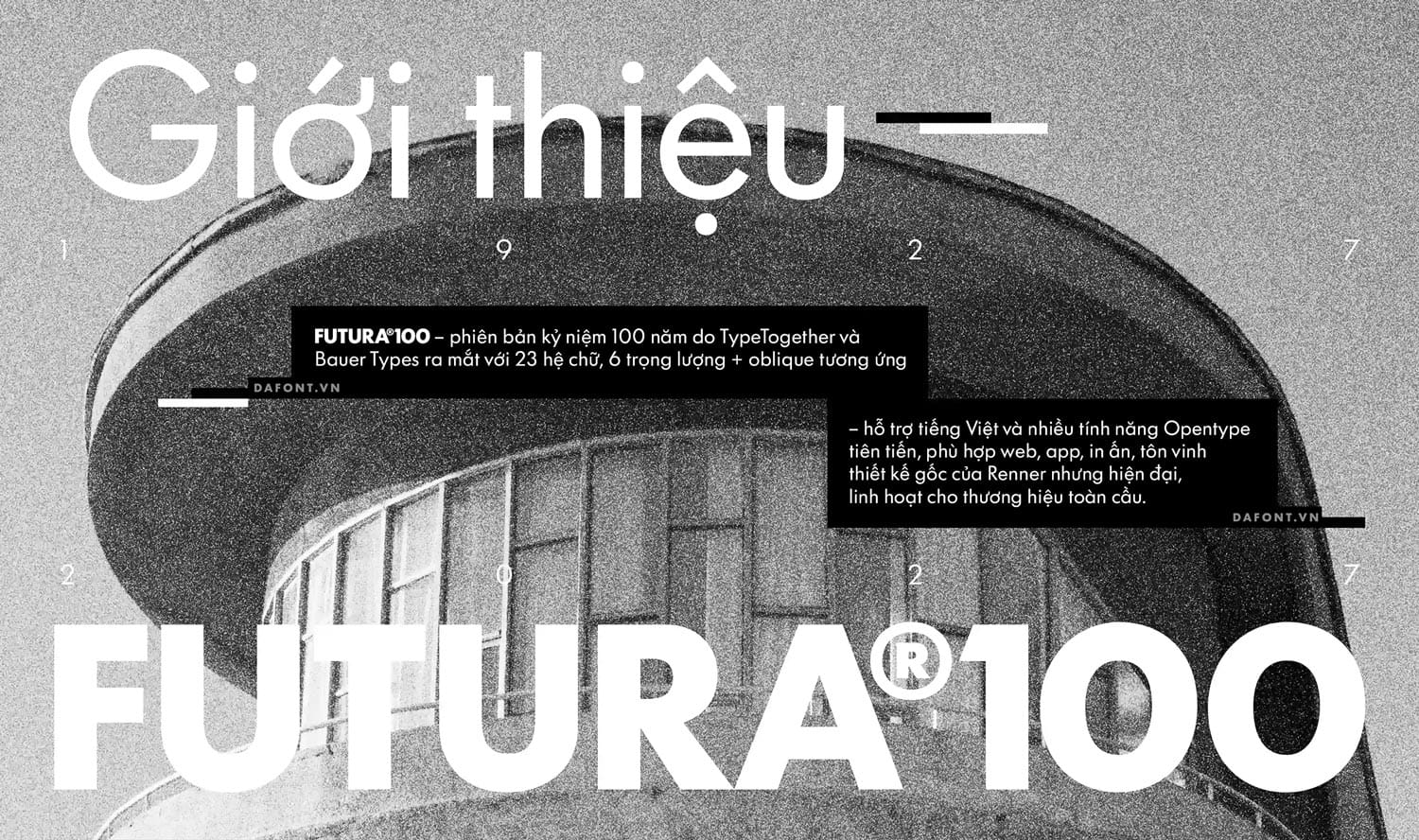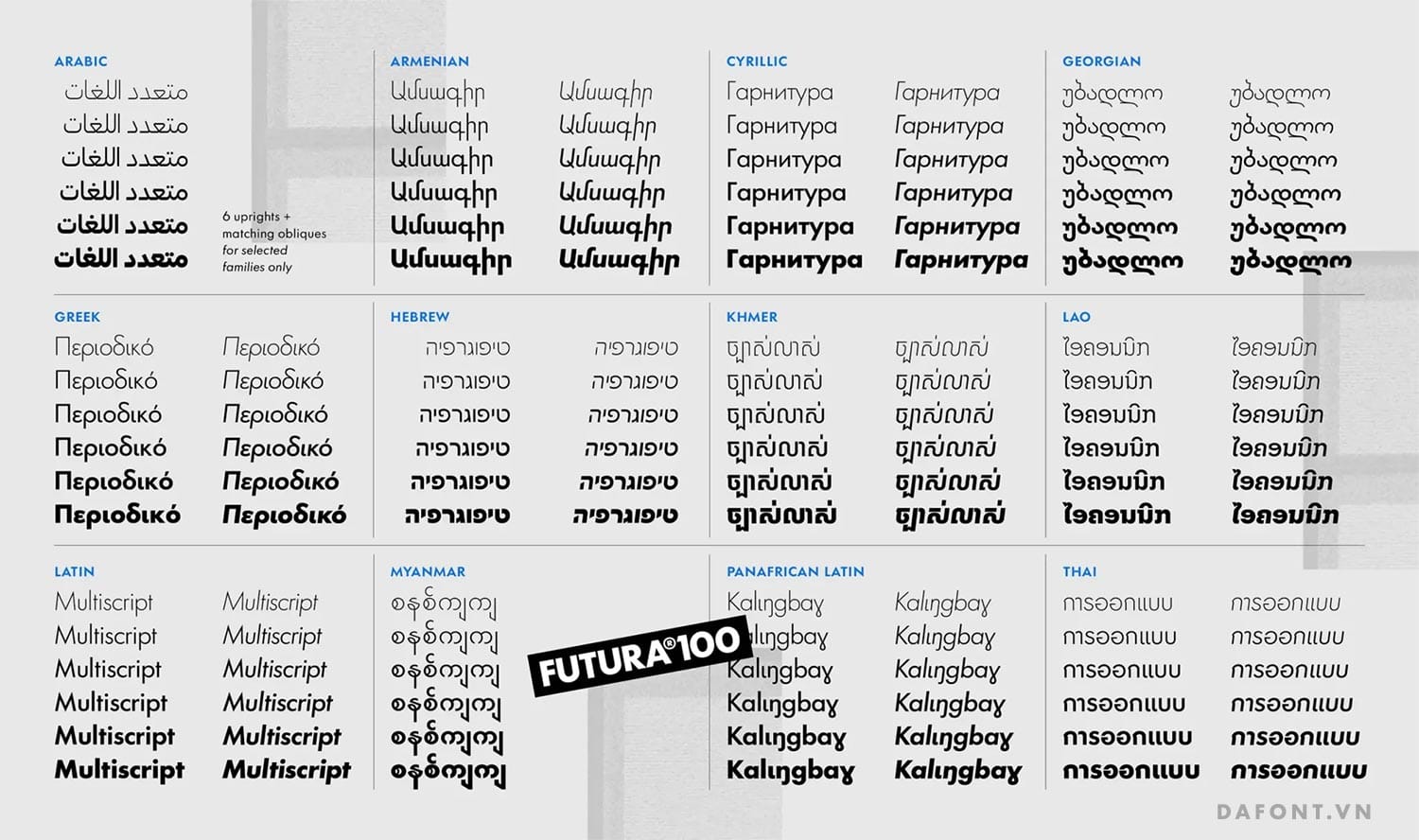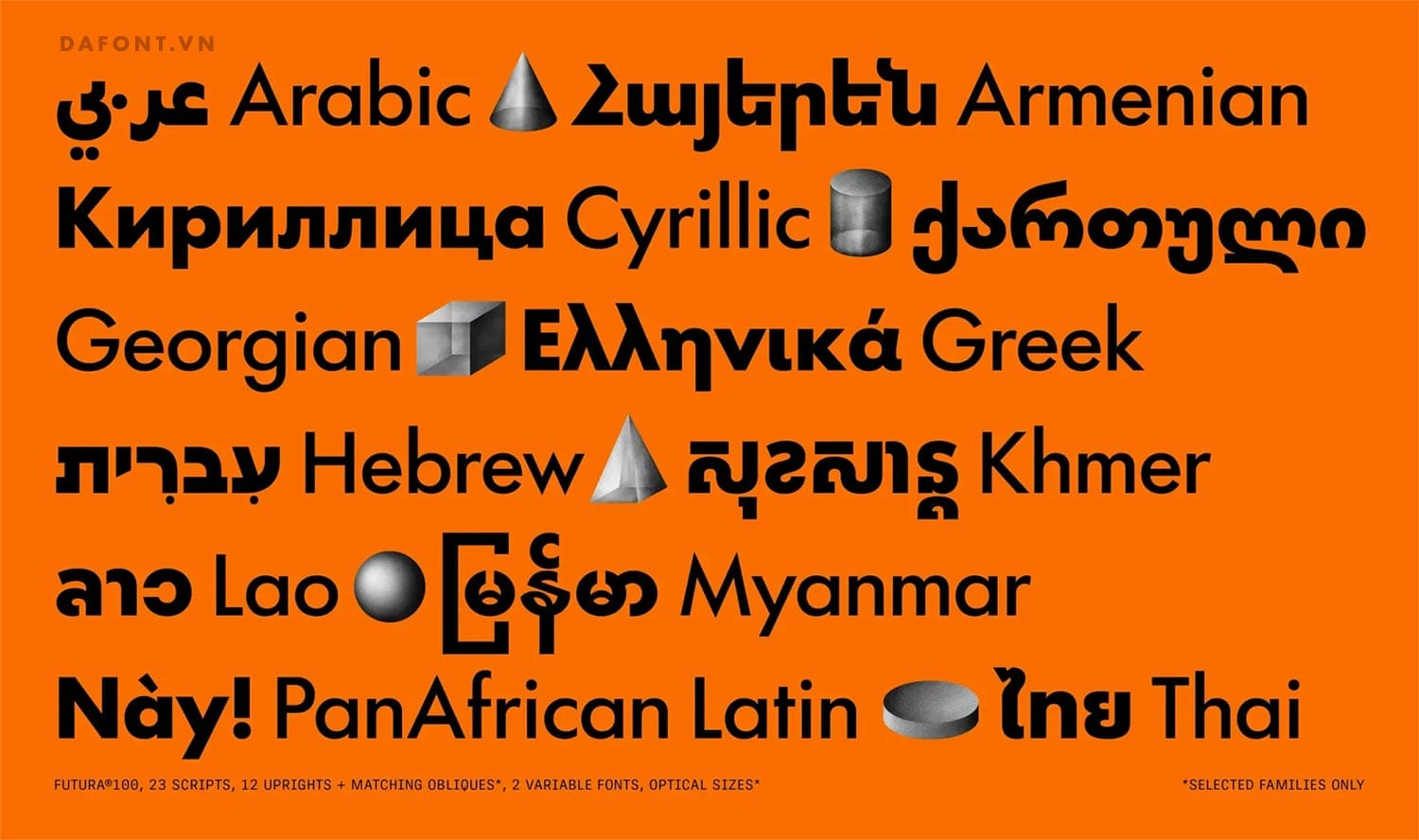
Futura100 là phiên bản Futura kỷ niệm 100 năm do TypeTogether hợp tác Bauer Types phát hành (9/2025). Bộ font bao gồm 12 hệ chữ lúc ra mắt, dự kiến mở rộng lên 23 có biến thể variable và optical size cho “Text”; 6 trọng lượng kèm oblique; hỗ trợ Latin mở rộng bao gồm tiếng Việt; nhiều tính năng OpenType hiện đại. Phù hợp branding toàn cầu, báo – tạp chí, UI và signage.
Sau 100 năm với số lượng hệ chữ hạn chế, thiết kế nguyên bản của Paul Renner cuối cùng đã được làm mới cho thời đại hiện nay. Futura100 gồm 23 hệ chữ (script), mỗi hệ chữ có 6 độ đậm nhạt khác nhau (Light, Book, Regular, Medium, Demibold, Bold). Phần lớn các hệ chữ này sẽ có phiên bản nghiêng (oblique) tương ứng, cũng như trục Optical Size (kích thước quang học) để tăng khả năng đọc. Với phạm vi ngôn ngữ bao phủ hơn 90% dân số thế giới, Futura100 mang đậm dấu ấn lịch sử, có thể áp dụng trên toàn cầu và toàn diện về mặt phong cách.
Futura nguyên bản từng là đỉnh cao của sans serif hình học, cô đọng thể loại này về các hình khối cơ bản và tối giản. Bauer Types và TypeTogether cho ra mắt Futura100 — tinh hoa của chữ hình học tối giản — đồng thời vẫn giữ trọn sự trung thành với dáng chữ gốc. Đây không phải là một bản nâng cấp, mà là sự mở rộng đúng nghĩa, tôn vinh ý tưởng gốc của Renner.
Futura100 – phiên bản Futura toàn cầu cho cho môi trường đa ngôn ngữ
Phiên bản mới là một dự án đồ sộ, mất gần hai năm nghiên cứu và thiết kế tỉ mỉ. Futura100 hiện hỗ trợ 12 hệ thống chữ viết, bao gồm tiếng Latin (dùng cho tiếng Anh và nhiều ngôn ngữ châu Âu), tiếng Cyrillic, tiếng Hy Lạp, tiếng Hebrew, tiếng Ả Rập và một số chữ viết châu Á và châu Phi. Mỗi hệ thống đều có nhiều độ đậm nhạt, kiểu chữ nghiêng tương ứng và một phiên bản đặc biệt được thiết kế để giúp việc đọc văn bản dài dễ dàng hơn. Ngoài ra còn có phiên bản phông chữ biến đổi, cho phép các nhà thiết kế dễ dàng điều chỉnh độ đậm nhạt và kiểu chữ cho bất kỳ dự án nào.
Theo như nhà phát triển, vào năm 2026, sẽ có thêm nhiều kiểu chữ được thêm vào, bao gồm các kiểu chữ chính của Ấn Độ, tiếng Trung giản thể và tiếng Hàn, cho phép Futura100 hoạt động với hơn 90% dân số thế giới và trở nên lý tưởng cho các thương hiệu toàn cầu, các công ty và bất kỳ ai muốn thiết kế của họ có giao diện nhất quán trên mọi ngôn ngữ và khu vực.
Futura100 cũng đi kèm với tất cả các tính năng bổ sung nhỏ như chữ hoa, dấu câu đặc biệt, nhiều kiểu số, mũi tên, chữ ghép và các điều chỉnh cụ thể cho từng chữ viết để làm cho mọi ngôn ngữ trông hoàn hảo.
Nhờ TypeTogether và Bauer Types, Futura100 hiện giúp việc tạo ra những thiết kế đẹp mắt, hiện đại, phù hợp với mọi nơi trên thế giới trở nên dễ dàng hơn bao giờ hết và cuối cùng, thiết kế và nghệ thuật luôn phải hướng đến sự hòa nhập.